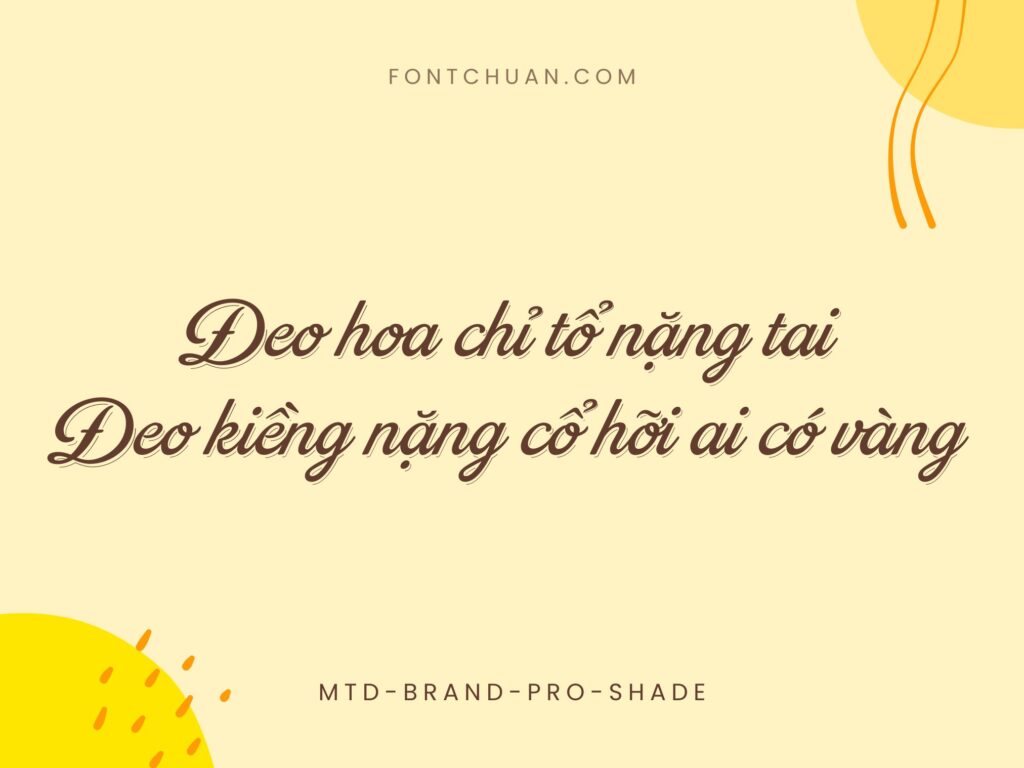
Font MTD Brand Pro là một kiểu chữ trang trí độc đáo, được thiết kế bởi Lián Types và đã được Việt hóa bởi Mộc Hạ. Bộ font này bao gồm nhiều phiên bản như Light, Regular, Inline, Shade và Ornaments, cung cấp sự đa dạng cho các thiết kế sáng tạo. Font hỗ trợ đầy đủ tiếng Việt cùng hơn 90 ngôn ngữ khác, mở rộng khả năng ứng dụng trong các dự án đa ngôn ngữ. Đây là một trong những phông chữ được cộng đồng thiết kế đánh giá cao và sử dụng trong nhiều dự án sáng tạo, đáp ứng nhu cầu đa dạng của người dùng.
MTD Brand Pro nổi bật với các đường nét tinh tế và phong cách trang trí đặc sắc, mang đến cảm giác sang trọng và nghệ thuật. Font rất phù hợp cho các thiết kế logo, tiêu đề, bao bì sản phẩm, thiệp mời và các ấn phẩm đòi hỏi sự tinh tế và độc đáo. Các ngành nghề phù hợp bao gồm quảng cáo, giáo dục, công nghệ, thiệp cưới và ảnh cưới. Font này cũng lý tưởng cho các sự kiện như Tết, Giáng sinh, Valentine và các lễ hội khác.